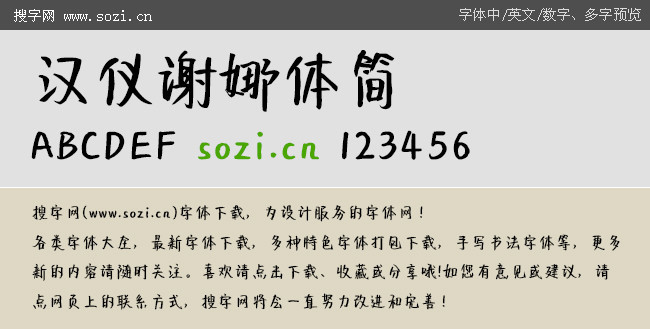
漢儀謝娜體簡
搜字網(wǎng)給大家提供一款漢儀謝娜體簡中文字體下載,娜字體也由漢儀推出,這款字體的筆畫非常干凈,清爽,偏楷書的風(fēng)格多一點,沒有多余的連筆,收放自如恰到好處。仔細看這一個個字,還能體會到可愛的氣息。這款字體稱得上是一款百變的字體,不同的人會看出不同的風(fēng)格,就像娜娜是個百變女神一樣。